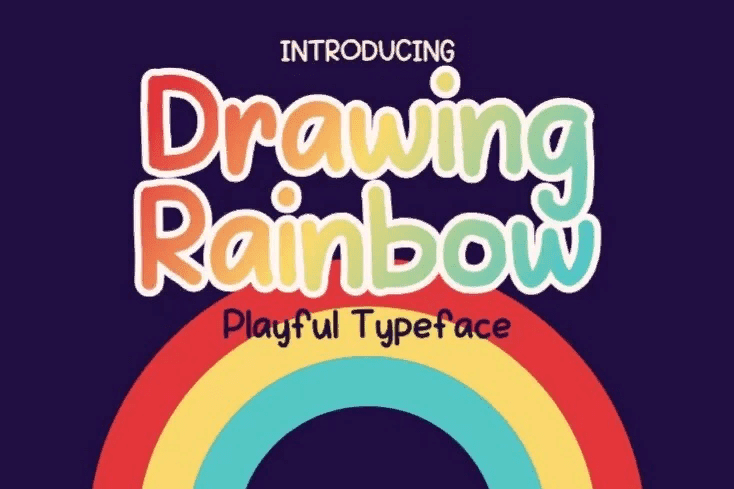
Название: Drawing Rainbow Font
Drawing Rainbow - это веселый дисплейный шрифт с концепцией радуги, которая приносит радость!
Этот шрифт выполнен в стиле глифов его оригинальных толстых линий, созданных вручную, чтобы создать по-настоящему естественное искусство.
Этот шрифт идеально подходит для логотипов, брендинга, продукции, обложек книг, детских книг, обучающих книг и многого другого.